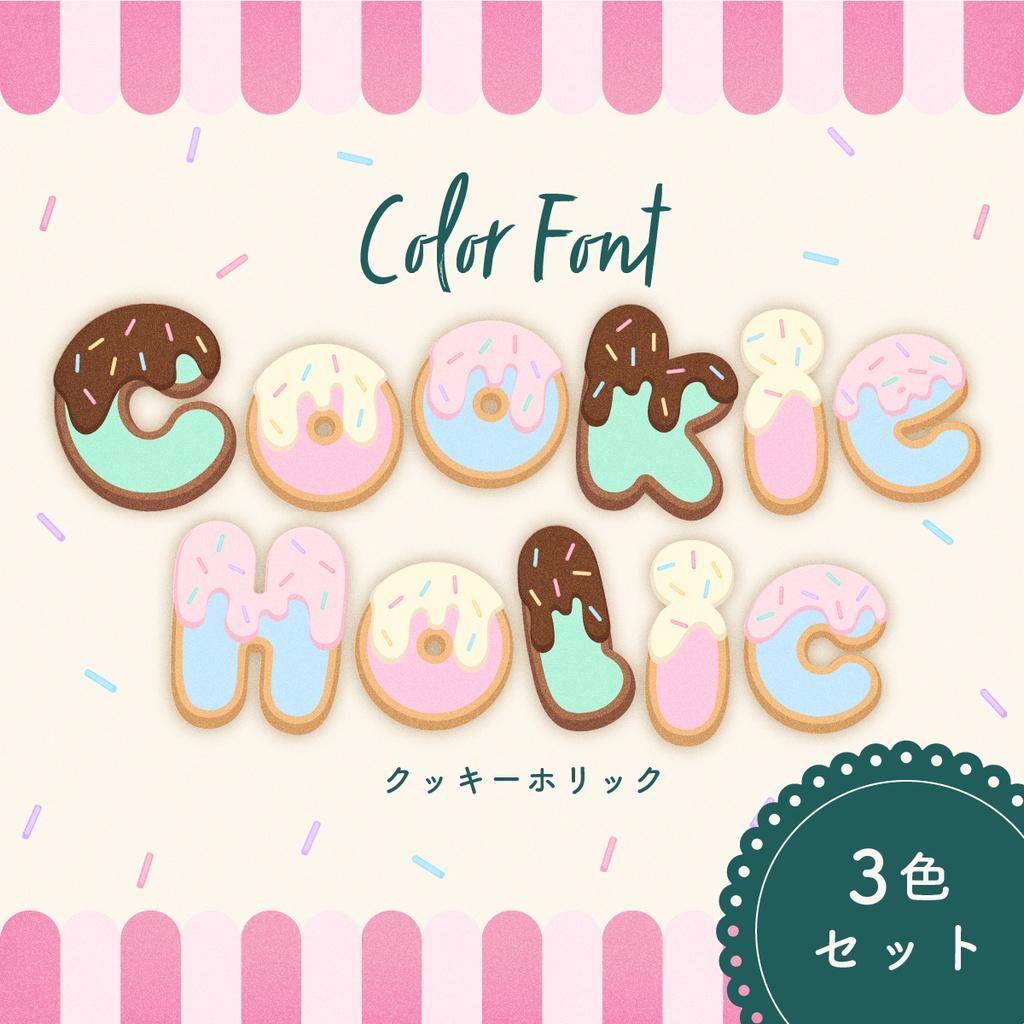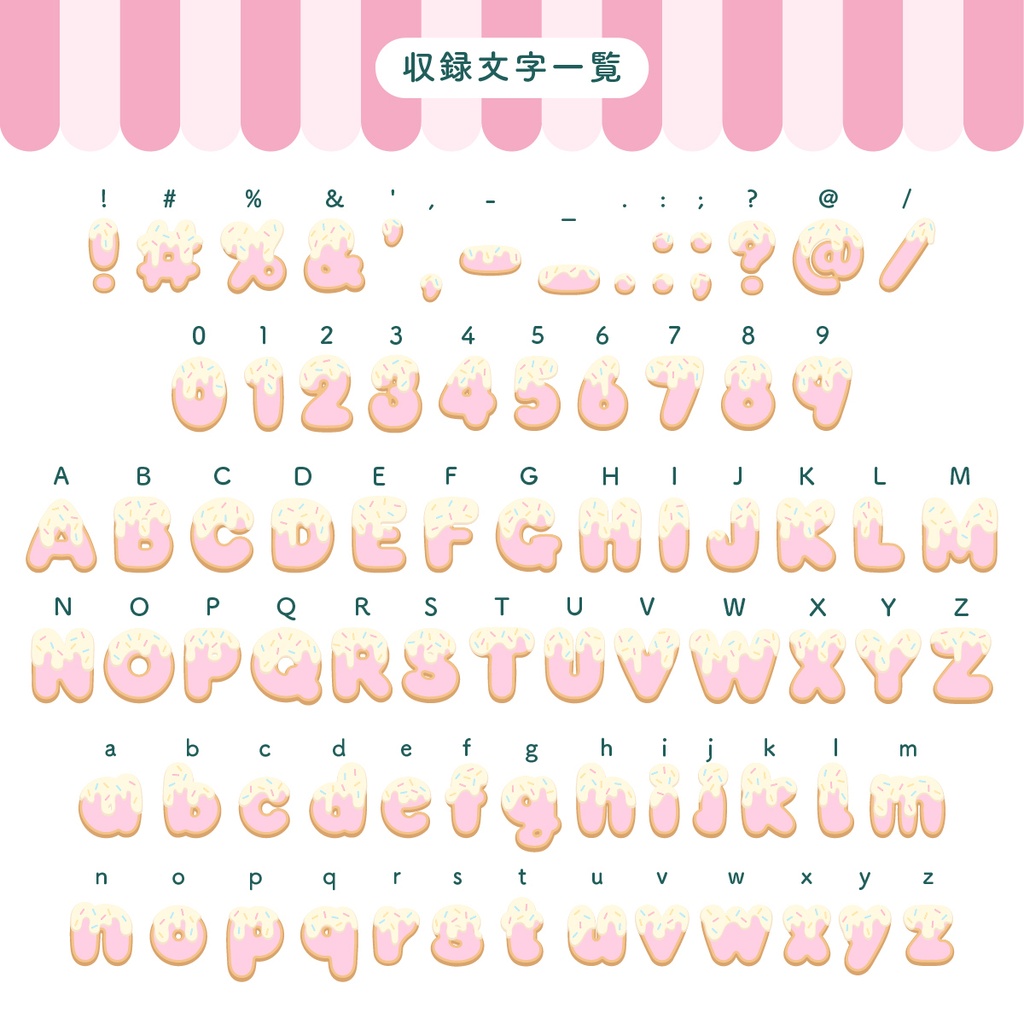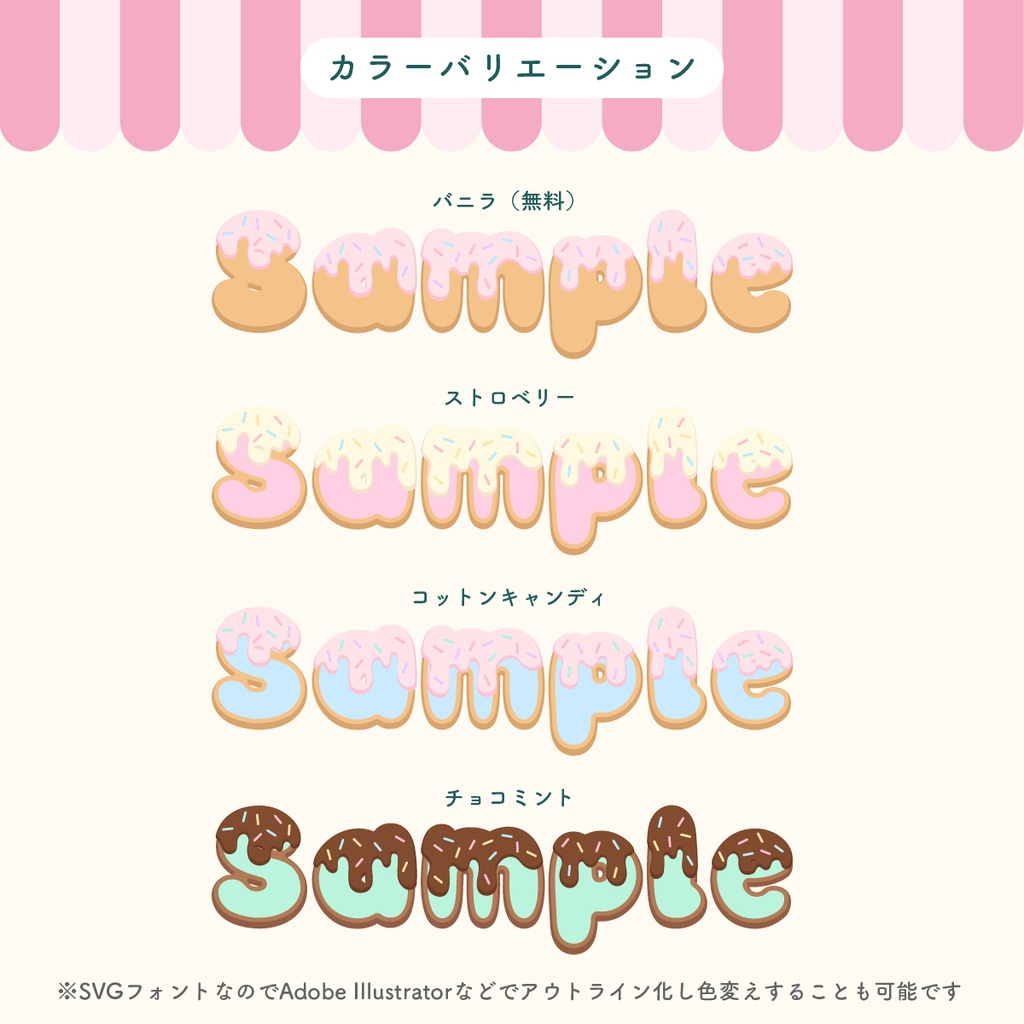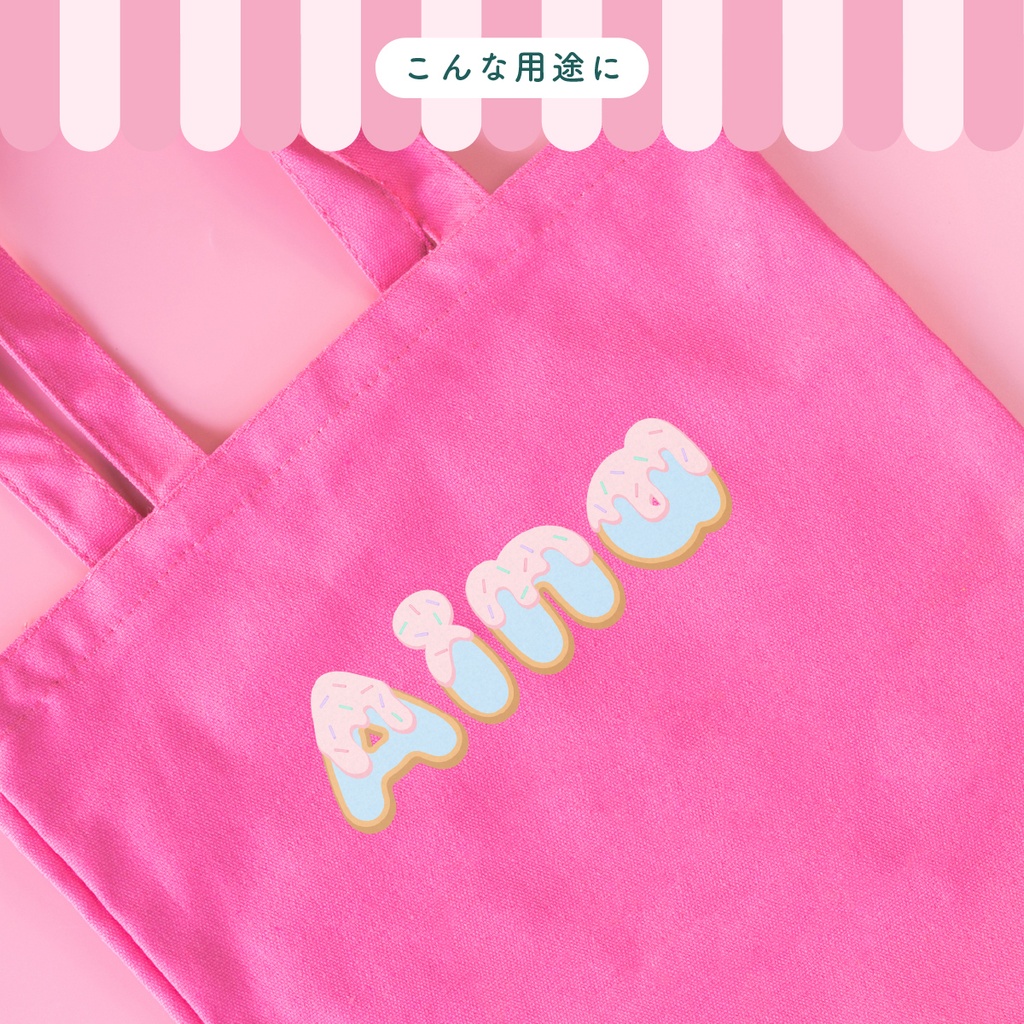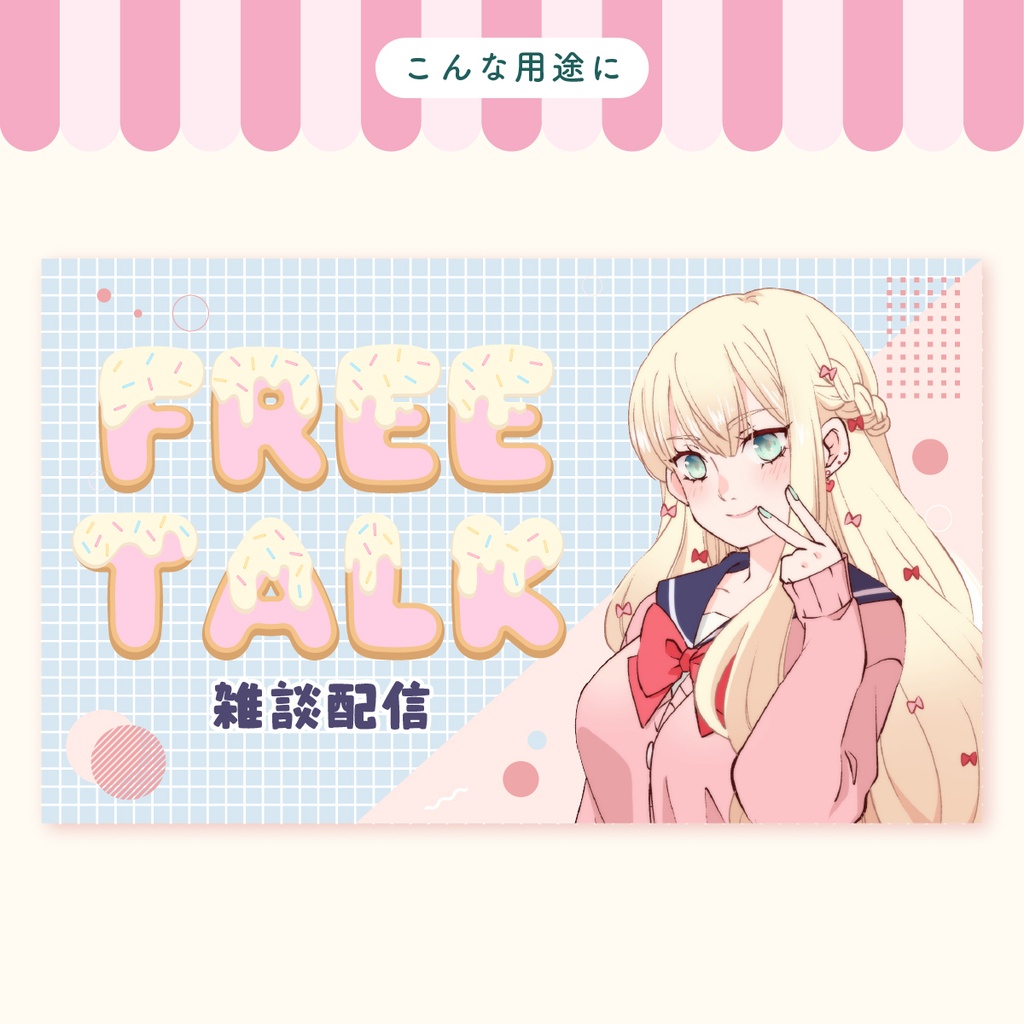
イラレやフォトショで使えるカラーフォントCookie Holic
クッキーをアイシングでデコレーションしたようなデザインを施したカラーフォントです。 Adobe Illustrator、Photoshop、InDesignで利用可能です。 お子様のお名前シールにしたり、応援うちわなどにいかがでしょうか? デザインに組み込む場合はここぞというときに使ってみてください。 無料版もご用意しています。(別ページ) カラーフォントが使用できる環境が限られているため、有料版をご購入の前に必ずお試しください。
英数、一部の記号を収録した欧文OpenType-SVGフォントです。 有料版には色違いのカラーフォント3つと、装飾の無いフォント(所謂普通のフォント)が含まれます。 SVGフォントなので、Illustratorなどでフォントをアウトライン化して色変えすることも可能です。 (有料版を購入せず、無料版を色変えしても問題ありません)